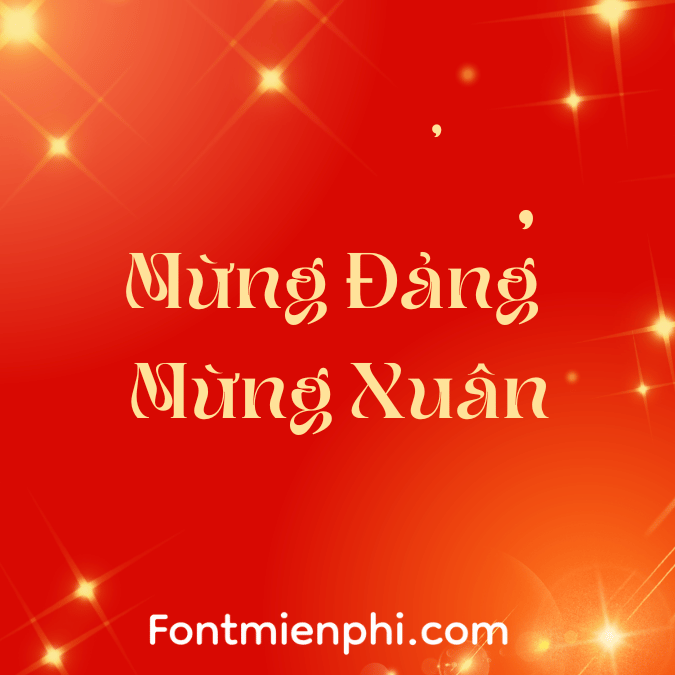
Giới thiệu Font Việt Hóa 1FTV VIP Meqanor
Font Việt Hóa 1FTV VIP Meqanor là một trong những loại font chữ nổi bật, được thiết kế đặc biệt để hỗ trợ người dùng Việt Nam trong việc sử dụng tiếng Việt trên các nền tảng số. Với kiểu dáng hiện đại và phong cách độc đáo, font chữ này không chỉ mang lại tính thẩm mỹ cao mà còn giúp cải thiện trải nghiệm đọc và viết.
Đặc Điểm Nổi Bật:
- Tính Thẩm Mỹ: Font Meqanor có thiết kế sang trọng, phù hợp cho nhiều mục đích sử dụng như thiết kế đồ họa, in ấn, và truyền thông trực tuyến.
- Hỗ Trợ Tiếng Việt: Font này được tối ưu hóa để hiển thị đầy đủ các ký tự tiếng Việt, bao gồm các dấu và chữ cái đặc biệt.
Lợi Ích Khi Sử Dụng Font 1FTV VIP Meqanor:
- Giao Diện Người Dùng Thân Thiện: Giúp người dùng dễ dàng truy cập và sử dụng cho các dự án cá nhân hoặc chuyên nghiệp.
- Thích Hợp Nhiều Ngành Nghề: Từ marketing đến giáo dục, font này có thể được áp dụng rộng rãi trong nhiều lĩnh vực khác nhau.
- Độ Đàn Hồi Cao: Chất lượng hình ảnh và độ rõ nét của font chữ giúp tăng cường tính chuyên nghiệp cho các tài liệu.
Kết Luận: